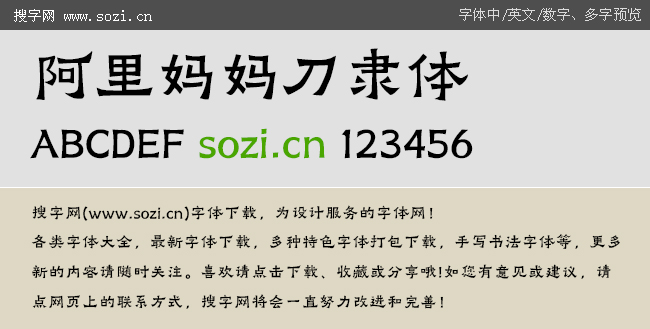
阿里媽媽刀隸體
搜字網給大家提供一款阿里媽媽刀隸體中文字體下載,阿里媽媽刀隸體,通過機器學習了爨寶子碑的精髓,強調了三角點折彎與橫畫兩端“雁尾”之方強,外露鋒芒,耀其精神,介于隸楷之間,保持著濃重的隸書方筆意味,給人以堅實、樸茂、稚拙、倔犟之感,打破常規常態的勻稱均衡,結字極為大膽,大小常常出人意料,看似失度,實則深得藝理,險中求正,靜中寓動,動中求靜。適合標題設計、海報設計、包裝設計等應用。